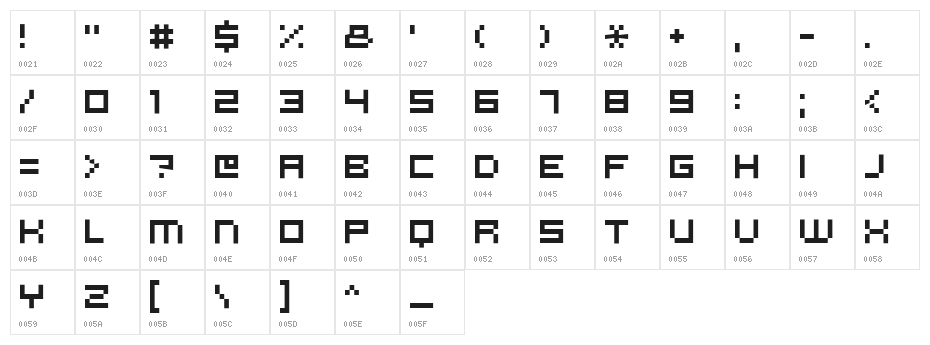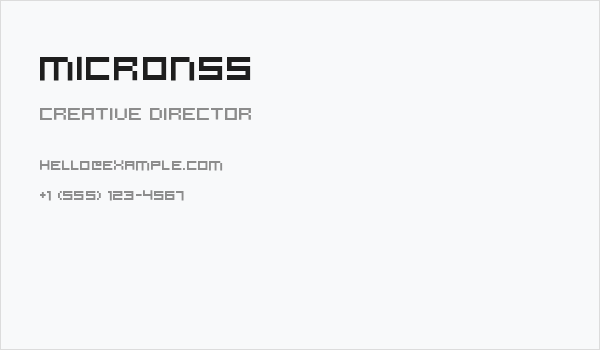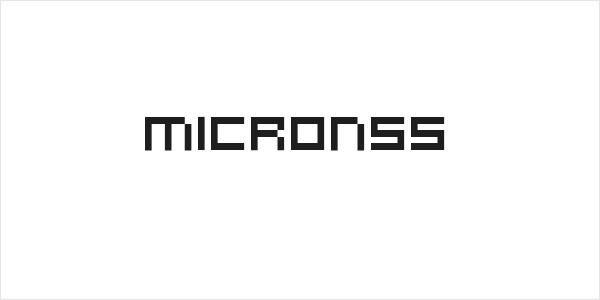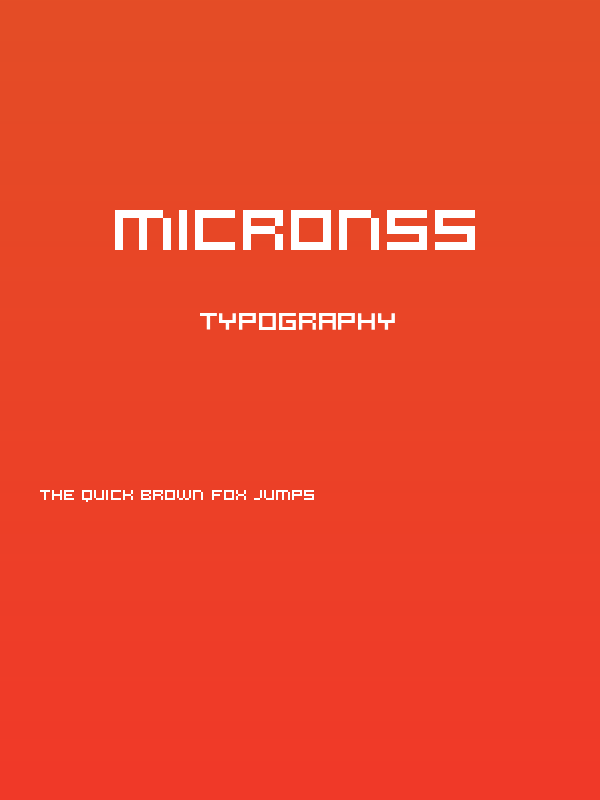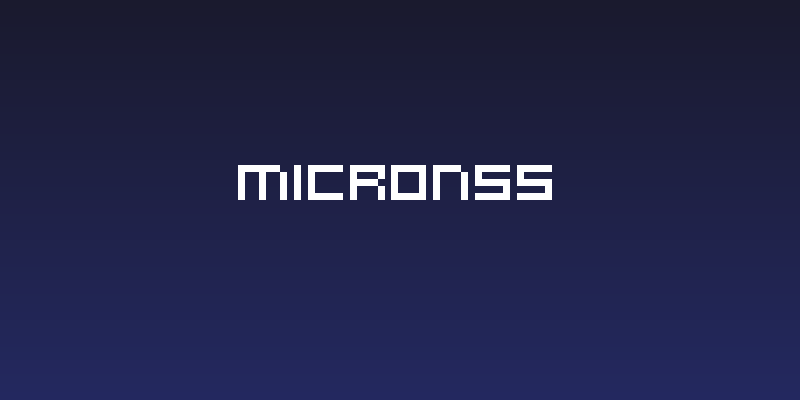
microN55 Font
| Gesamtstil | Retro, Digital |
| Anwendungsfall | Headlines, Logos, Digital displays |
| Vorgeschlagene Projekte | Ideal for video game design, tech-themed posters, digital art projects, and retro-themed branding. |